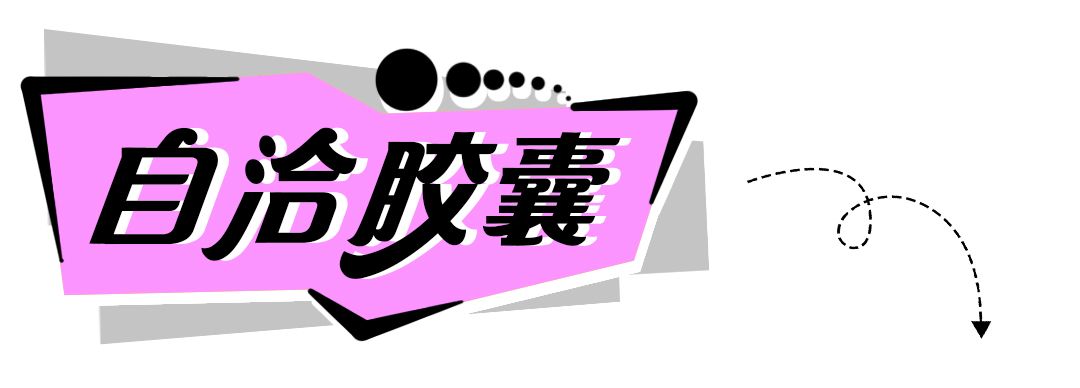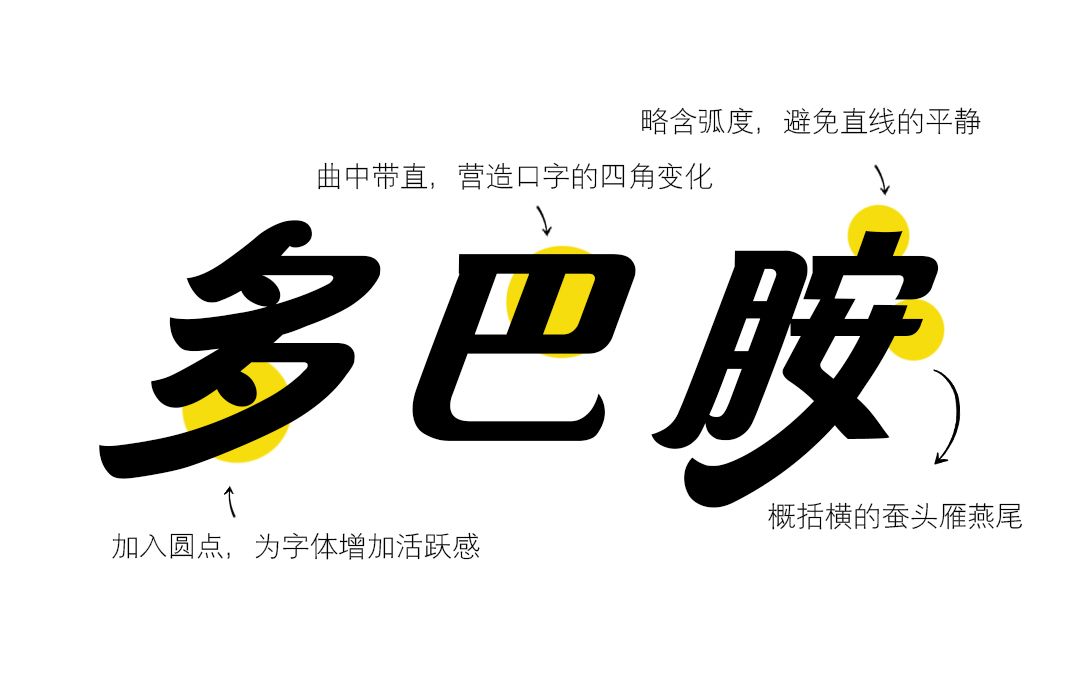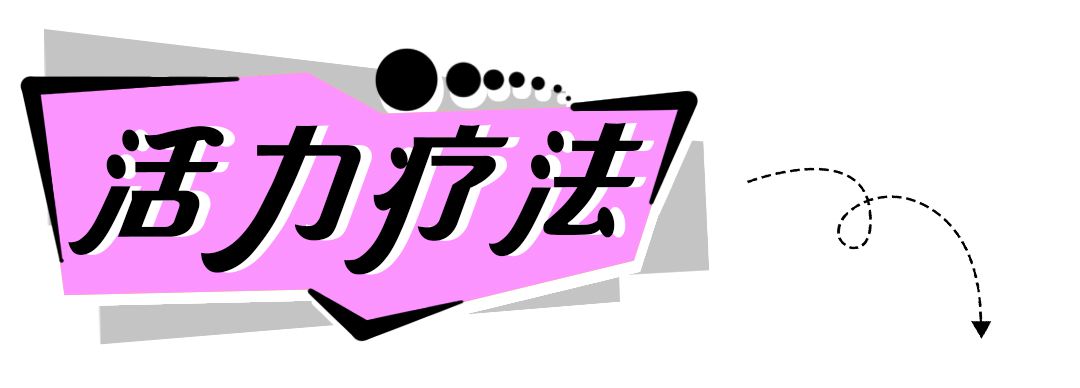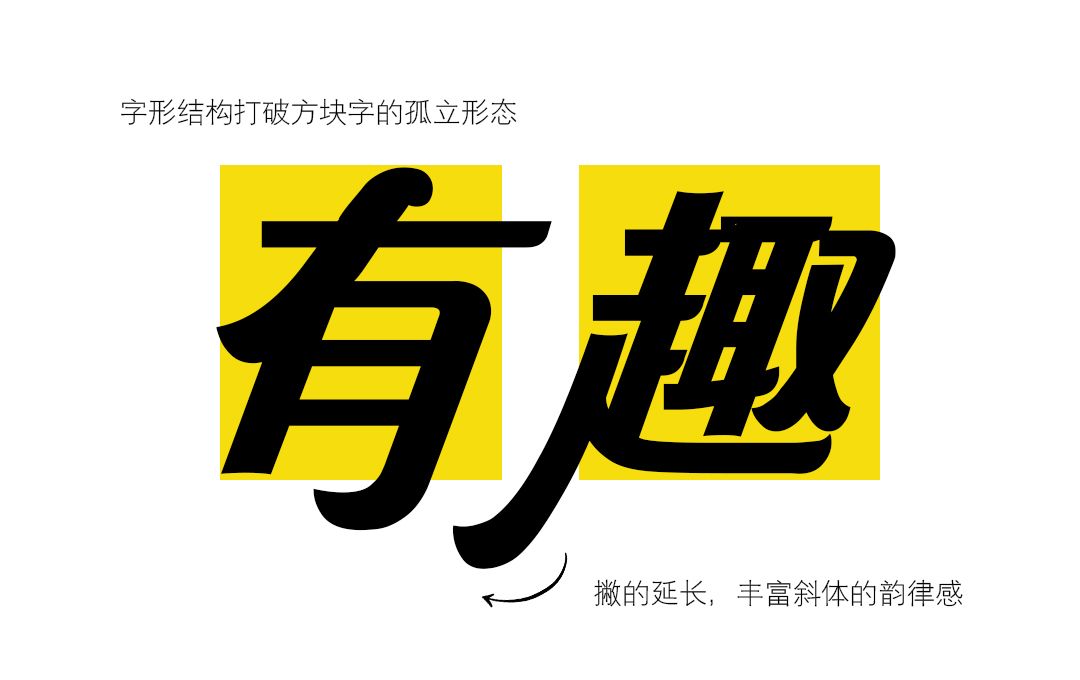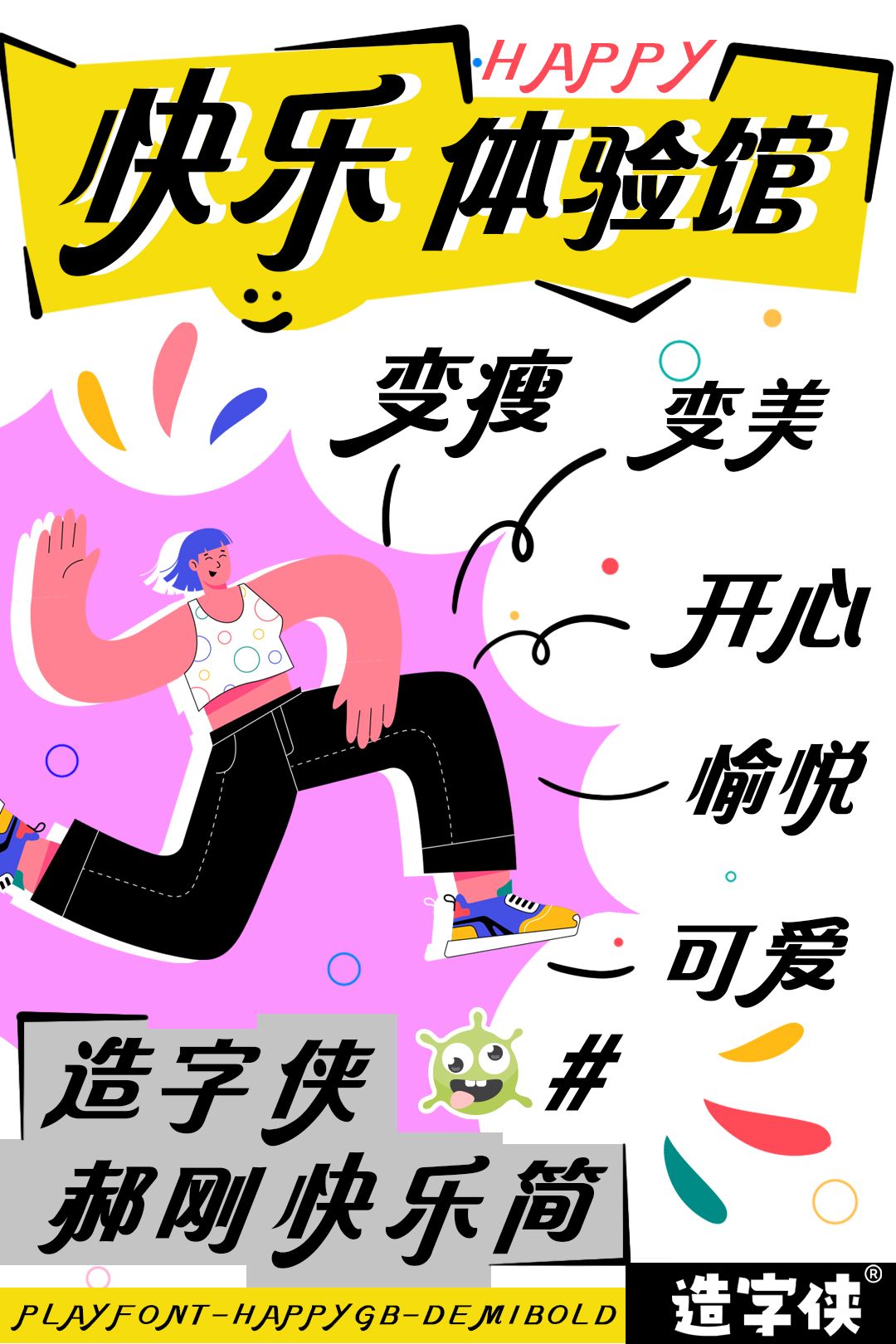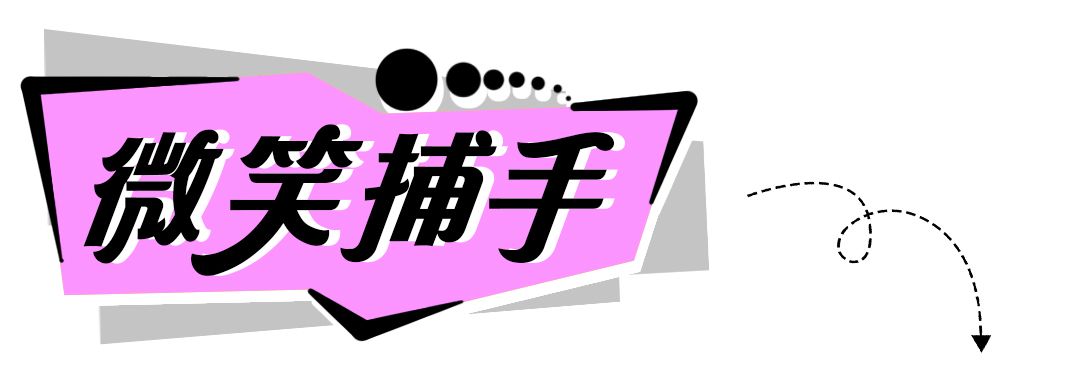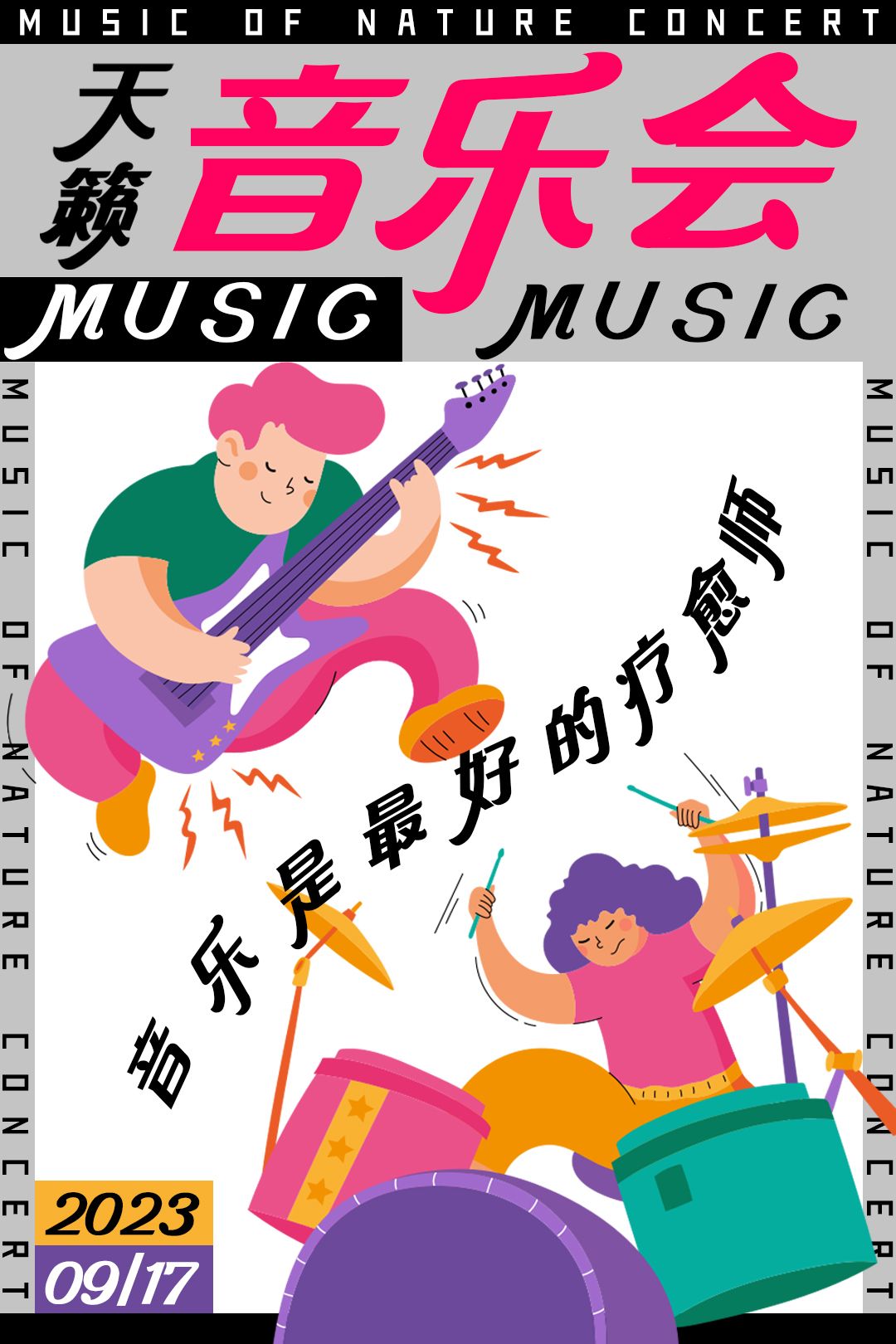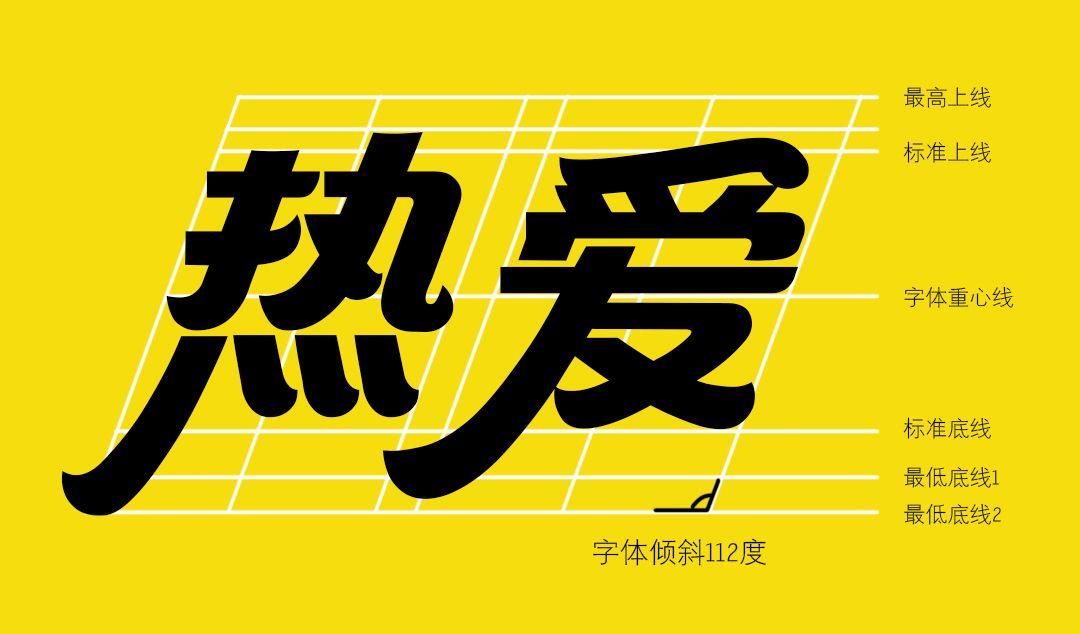
字造快乐 | 让人变快乐乐乐乐乐的情绪类字体——造字侠郝刚快乐简
充满焦虑和竞争的成人世界,情绪问题成为时代危机,无处不在的内卷卷卷卷卷到人心累。
快乐是情绪的止痛剂,在字体中加入快乐情绪,会发生什么样的奇妙反应呢?励字造梦共创字库首创引发快乐联想的情绪类字体——造字侠郝刚快乐简,反卷达人,快乐至上,跟烦恼说拜拜。
采用中西结合的设计手法,一方面糅合西文斜体装饰风格的浪漫优雅,字体倾斜112度;一方面运用汉字隶书笔画的撇、捺错落变化,在蚕头燕尾的韵味中,构建斜体字的韵律感、节奏感;在微妙的平衡感中,创造轻松明快的自洽节奏,也是对字体美感的均衡把控。
字形结构打破方块字的孤立形态,重心右移,使字体搭建独特的空间结构。撇的延长,丰富斜体的韵律感,给字体全新的支点;左右点的设计,打破常规对称的呆板,使字体更为欢快活泼、更有生命力。
造字侠郝刚快乐简独特的字形特征,给人清新、流畅、优雅的视觉享受。活泼、动感的斜体韵律,让人忍不住弯起眼睛、翘起嘴角,笑出快乐。